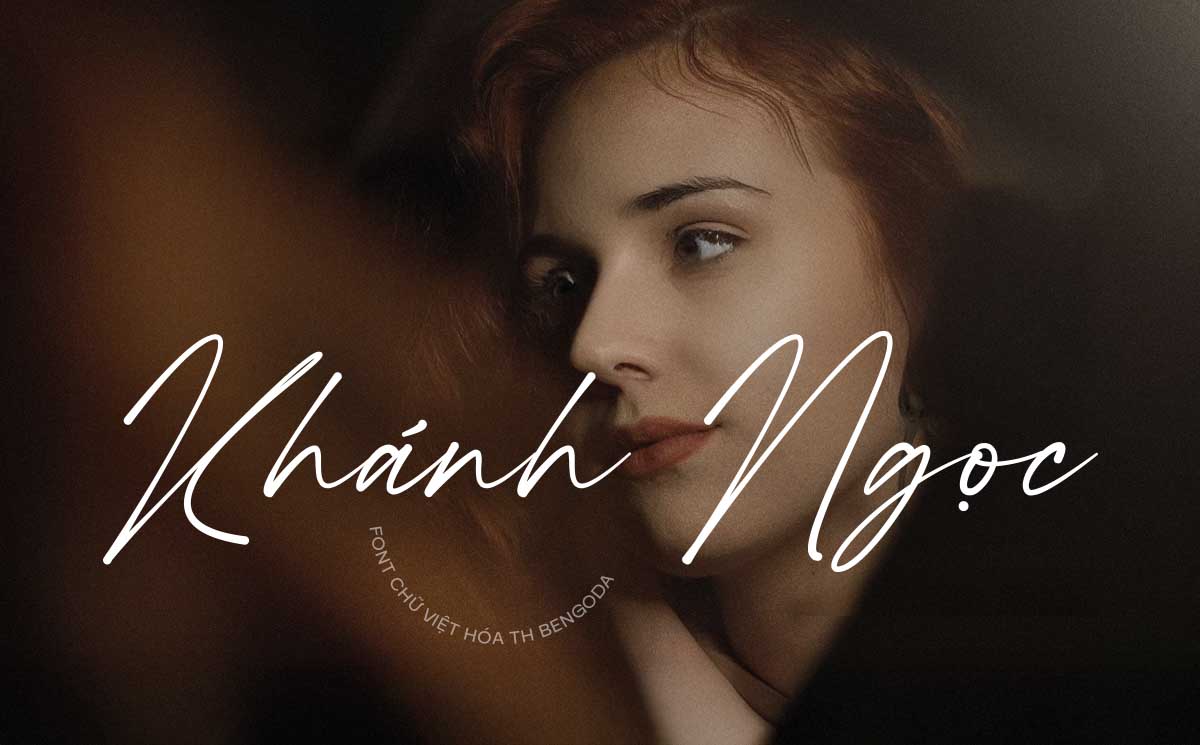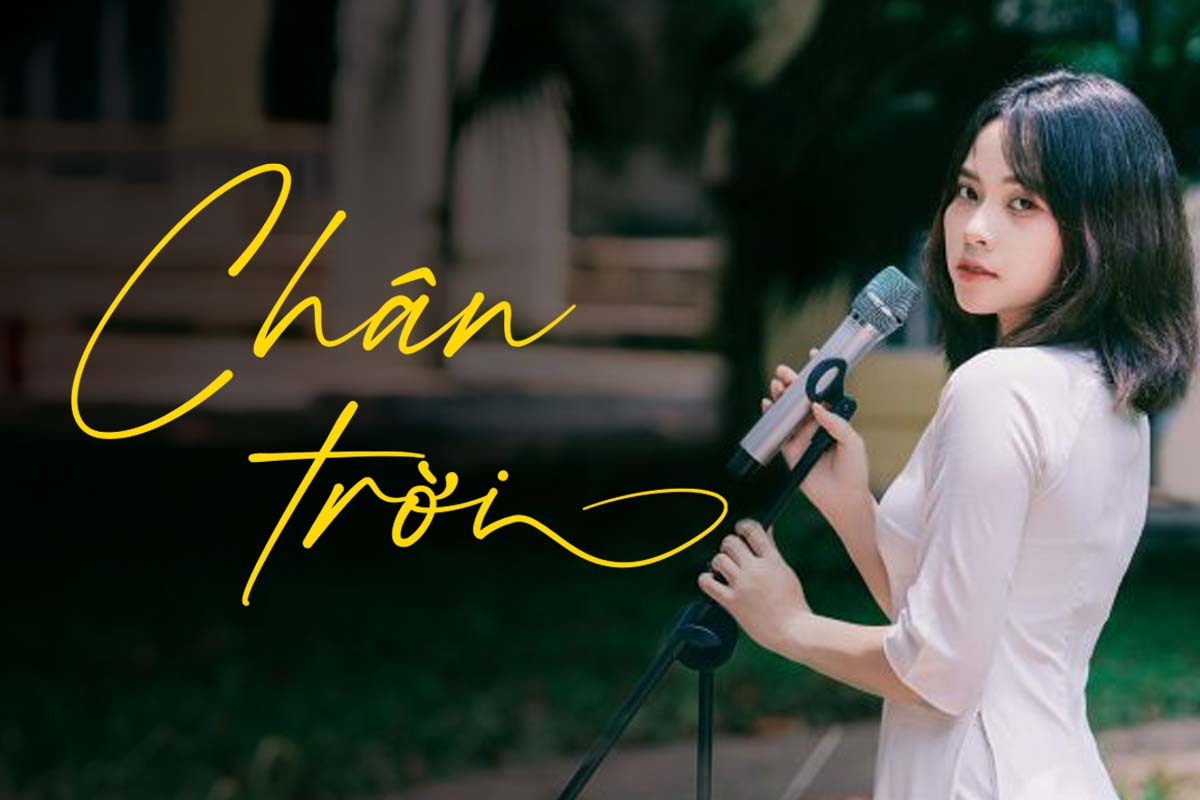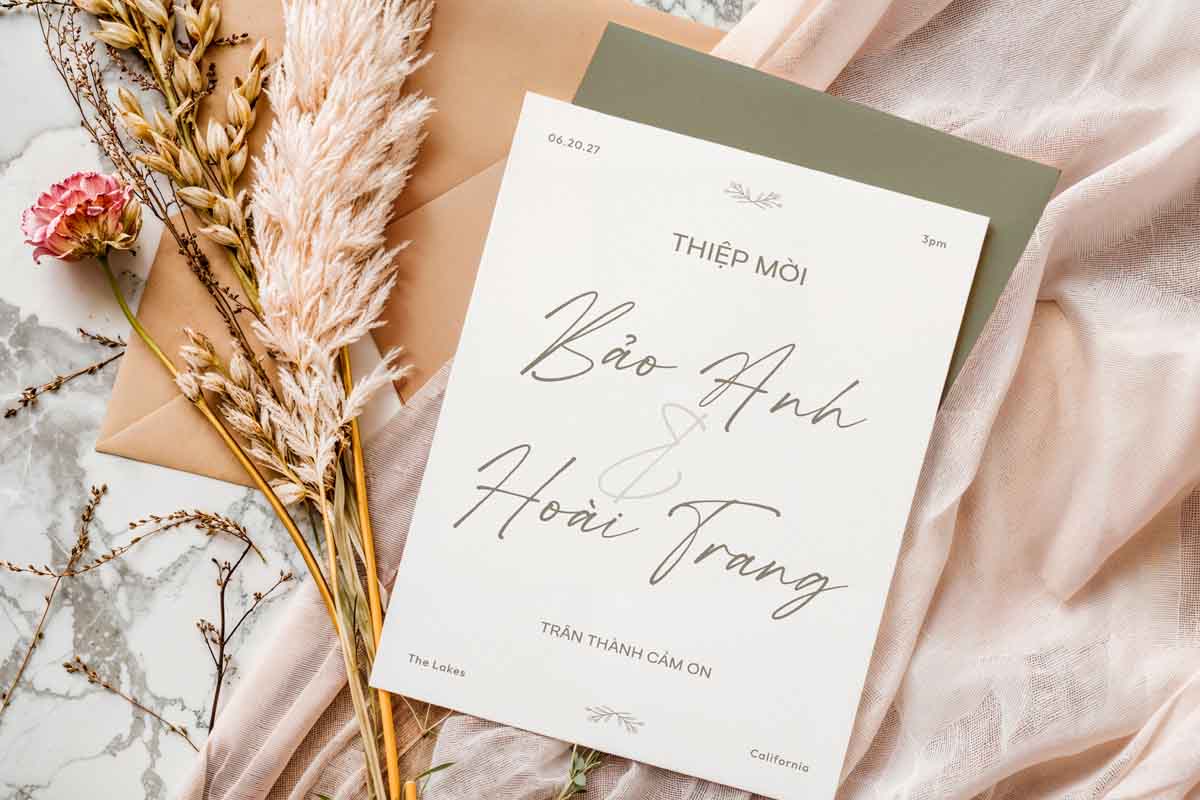
TH Bengoda – Font Chữ Ký Đẹp Việt Hóa Mềm Mại
Trong thế giới thiết kế hiện đại, font chữ ký (signature script) luôn là lựa chọn lý tưởng để tạo ra sự tinh tế, cá nhân hóa và cảm xúc trong từng chi tiết. Hôm nay, tôi xin giới thiệu đến bạn một bộ font đặc biệt: TH Bengoda – phiên bản Việt hóa từ font gốc Bengoda của Rantautype Studio.
Font chữ này được tôi Việt hóa thủ công, chỉnh sửa tỉ mỉ toàn bộ hệ thống dấu tiếng Việt. Tất cả dấu thanh (sắc, huyền, hỏi, ngã, nặng) và nguyên âm đều được tối ưu để không bị lỗi hiển thị, không dính ký tự, đảm bảo đẹp mắt và hài hòa trong mọi kích thước và nền tảng sử dụng.
Nguồn gốc và phong cách của font Bengoda
Bengoda là một thiết kế font chữ viết tay cao cấp đến từ Yudi Pratama Chandra – nhà sáng lập Rantautype Studio. Phong cách của Bengoda mang đậm chất “chữ ký hiện đại” với các nét chữ uyển chuyển, mềm mại và hơi nghiêng nhẹ sang phải, tạo cảm giác như được viết bằng bút mực thật.
Bộ font này rất phù hợp cho các dự án cần tính thẩm mỹ và nghệ thuật cao như:
• Thiết kế logo thương hiệu cá nhân
• Thiệp cưới, thiệp cảm ơn
• Bìa sách, tiêu đề tạp chí
• Chữ ký ảnh watermark
• Bao bì mỹ phẩm, thời trang
TH Bengoda – Chất lượng Việt hóa tối ưu cho thiết kế chuyên nghiệp
Là một nhà thiết kế chuyên làm việc với tiếng Việt, tôi hiểu rõ những khó khăn khi sử dụng font chữ ký không hỗ trợ dấu tiếng Việt đầy đủ. Vì vậy, với TH Bengoda, tôi đã:
• Tối ưu toàn bộ dấu tiếng Việt (bao gồm các ký tự ă, â, ê, ô, ơ, ư, đ…)
• Chỉnh sửa vị trí dấu thanh để không bị che khuất hoặc lệch khỏi trục chính
• Giữ nguyên vẻ đẹp mềm mại, bay bổng nhưng vẫn đảm bảo tính ứng dụng cao trong thiết kế thực tế
Bạn hoàn toàn có thể sử dụng font cho cả in ấn và thiết kế số, với tỷ lệ hiển thị sắc nét trên mọi loại thiết bị.
Tính ứng dụng và cảm hứng thiết kế từ TH Bengoda
Phong cách viết tay tự nhiên của TH Bengoda giúp các thiết kế trở nên gần gũi, tinh tế và chuyên nghiệp. Đặc biệt, đường nét chữ dài, cong mềm ở các ký tự như “y”, “g”, “f” hay “h” mang lại cảm giác tự do, cá tính nhưng vẫn rất “có gu”.
Những thương hiệu thiên về lifestyle, làm đẹp, thời trang, cá nhân hóa chắc chắn sẽ yêu thích font chữ này. Font cũng rất lý tưởng cho các trích dẫn truyền cảm hứng, tiêu đề blog hoặc các ấn phẩm thiết kế theo phong cách thủ công (handmade).
TH Bengoda không chỉ là một font chữ – mà còn là công cụ truyền cảm xúc trong thiết kế. Với sự kết hợp hoàn hảo giữa nét viết tay nghệ thuật và khả năng hỗ trợ tiếng Việt tối ưu, bạn có thể dễ dàng tạo nên những sản phẩm thiết kế mang dấu ấn cá nhân sâu sắc.